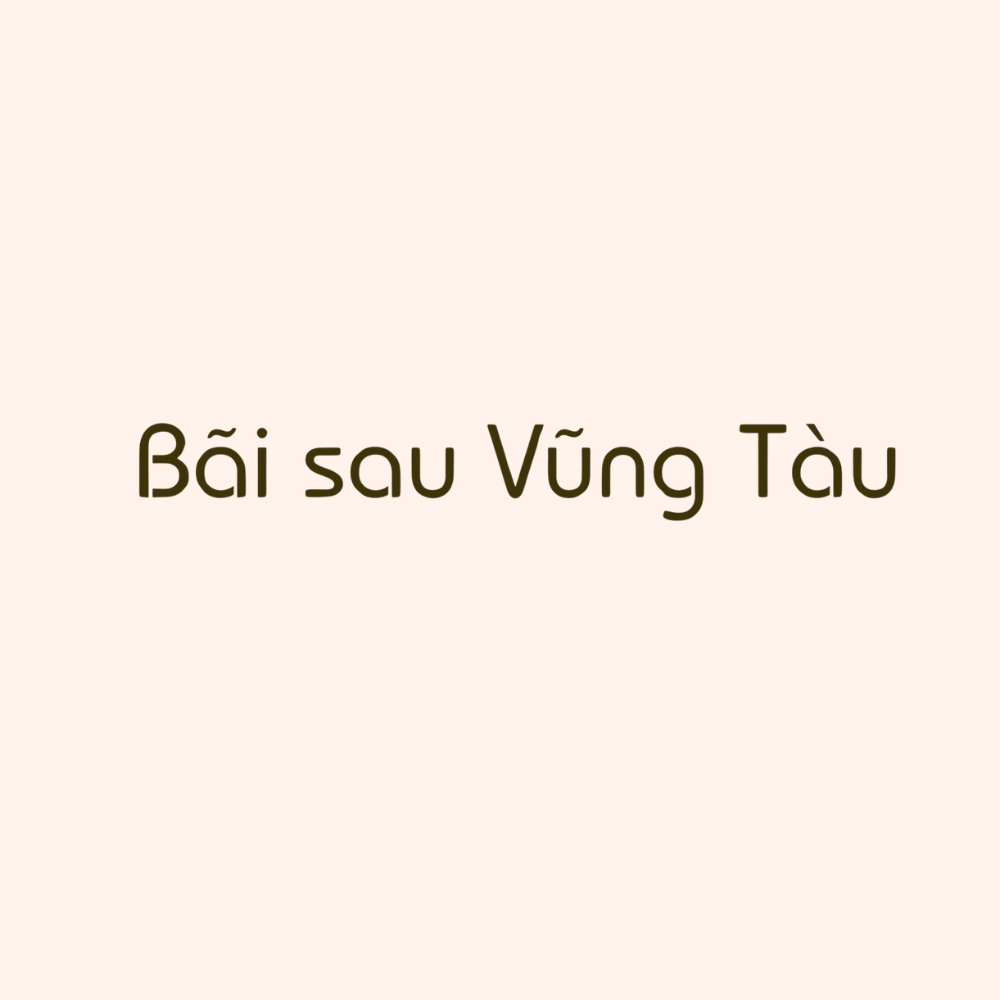
Trong hệ thống font chữ tiếng Việt, bộ UVN (Ủy ban Việt ngữ hóa) từ lâu đã trở thành một chuẩn mực nhờ khả năng hiển thị dấu thanh ổn định và đa dạng về phong cách. Trong đó, font Việt hóa UVN Bai Sau nổi bật với diện mạo gọn gàng, mang hơi thở của sự tối giản nhưng vẫn đầy tinh tế.
Đặc điểm của font Việt hóa UVN Bai Sau trong thiết kế chuyên nghiệp
Nét chữ của UVN Bai Sau sở hữu cấu trúc hình học cân đối, giúp tạo ra sự thông thoáng cho các đoạn văn bản trình bày. Điểm đáng chú ý của font chữ hiện đại UVN Bai Sau Việt hóa chính là tính ứng dụng đa năng, từ việc làm tiêu đề nổi bật cho đến việc hiển thị các đoạn nội dung chi tiết. Bản Việt hóa chuẩn mã Unicode giúp loại bỏ các rủi ro về lỗi ký tự, giúp quá trình triển khai ý tưởng từ bản vẽ thiết kế đến ấn phẩm in ấn diễn ra thuận lợi.
Sự ổn định trong thiết kế của bộ font này còn giúp người xem dễ dàng tiếp nhận thông tin mà không bị mỏi mắt. Đối với các dự án xây dựng, nơi các thông số và chỉ dẫn cần sự rõ ràng, UVN Bai Sau là lựa chọn phù hợp để duy trì tính thẩm mỹ mà không làm mất đi tính thực dụng. Đây là công cụ hữu ích cho những ai đang tìm kiếm vẻ đẹp hiện đại, trung tính cho các sản phẩm sáng tạo của mình.
| Phân loại phong cách | Sans-serif / Modern Style |
| Nhóm font liên quan | UVN Bai Sau, UVN Bai Sang Nang |
| Mục đích phù hợp | Thuyết minh dự án, Ghi chú kỹ thuật, Web |
Tư vấn trình bày: Để tạo nên sự phân cấp thông tin rõ ràng, bạn có thể sử dụng kiểu font uvn bai sang nang viet hoa (biến thể đậm) cho các tiêu đề chính và dùng UVN Bai Sau cho phần nội dung mô tả chi tiết.
03 Ứng dụng thực tế của font chữ hiện đại UVN Bai Sau Việt hóa
Với vẻ ngoài chuyên nghiệp và sự rõ ràng trong cấu trúc nét, bộ font này mang lại giá trị thực tế khi được ứng dụng vào các khâu vận hành và trang trí công trình:
03 Lưu ý khi sử dụng bộ font UVN Bai Sau
Để duy trì hiệu quả thị giác và tính chuyên nghiệp cho bản thiết kế, người dùng nên lưu tâm một số kinh nghiệm kỹ thuật sau:
- Cân đối khoảng cách dòng: Do cấu trúc chữ hiện đại có xu hướng gọn gàng, bạn nên thiết lập khoảng cách dòng thoáng một chút để văn bản không bị bết dính khi in ấn trên các khổ giấy nhỏ như A4 hoặc brochure.
- Phối hợp font chữ hài hòa: UVN Bai Sau hoạt động ổn định khi đi cùng một font Serif mảnh nếu bạn muốn tạo ra sự tương phản giữa nét cổ điển và hiện đại trong cùng một hồ sơ dự án.